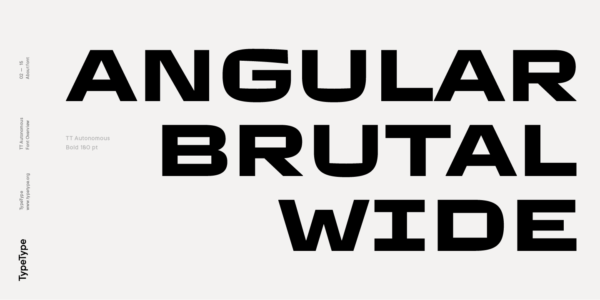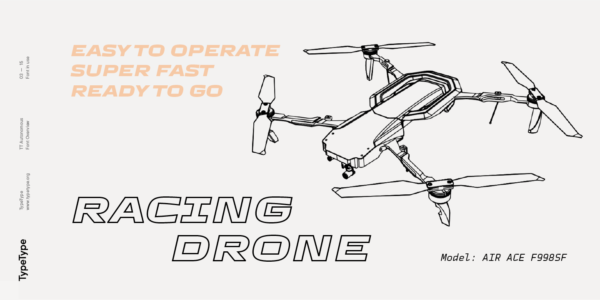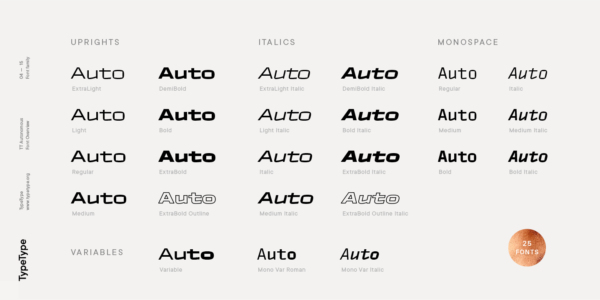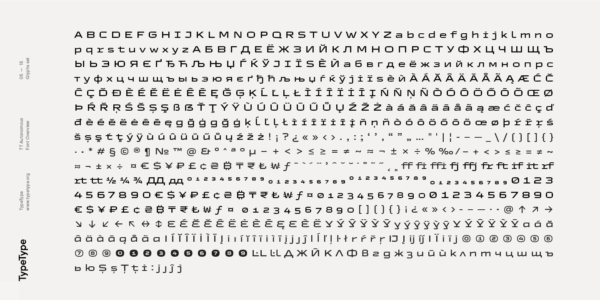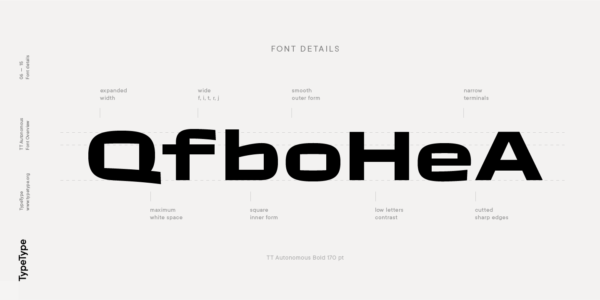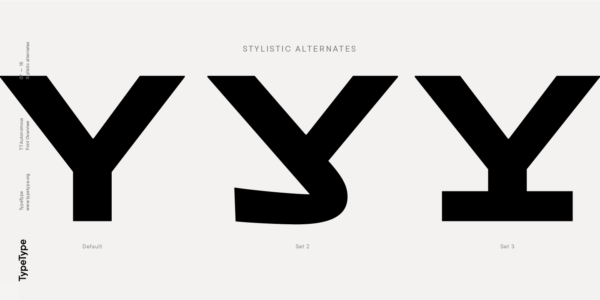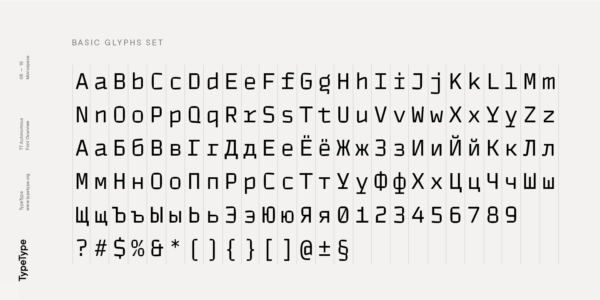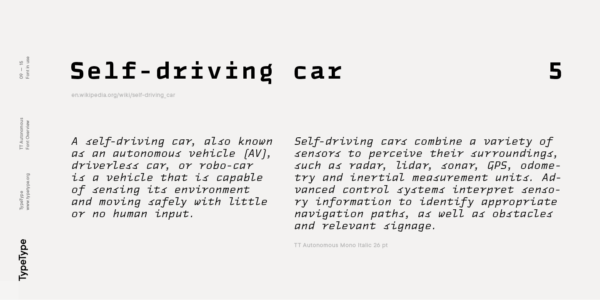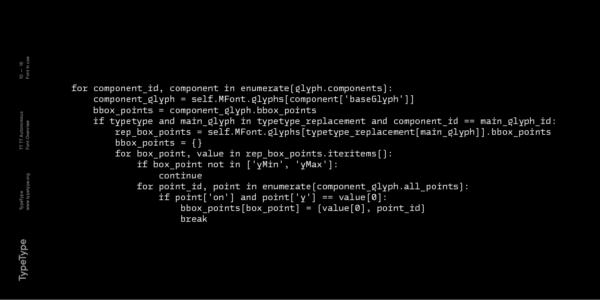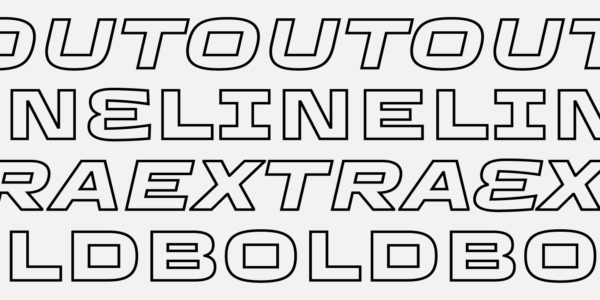
TT Autonomous
TT Autonomous — ТТ Отонамус
Произносится «ТТ Отонамус». «Autonomous» в переводе с английского «автономный». Буквы «TT» являются аббревиатурой названия компании.
TT Autonomous — брутальный технологический гротеск со сквадраченными формами. В гарнитуру входит моноширинное подсемейство, которое можно использовать для кодинга.
Современный брутальный технологичный гротеск
Идея проекта зародилась в Амстердаме, когда одна из наших коллег ехала на официальном электрическом такси аэропорта Схипхол. В тот момент мы как раз размышляли о создании нового широкого гротеска и во время этой поездки вдруг возник интересный вопрос — а какой шрифт мог бы ассоциироваться с электрическим беспилотным транспортом и, кроме того, хорошо дополнить эту тему с визуальной точки зрения.
В гарнитуре TT Autonomous есть вариативная версиякак обычной гарнитуры, так и моноширинного семейства.
14 начертаний, 6 моно, 2 аутлайн и 3 вариативных шрифта
О гарнитуре TT Autonomous
Идея проекта зародилась в Амстердаме, когда одна из наших коллег ехала на официальном электрическом такси аэропорта Схипхол. В тот момент мы как раз размышляли о создании нового широкого гротеска и во время этой поездки вдруг возник интересный вопрос — а какой шрифт мог бы ассоциироваться с электрическим беспилотным транспортом и, кроме того, хорошо дополнить эту тему с визуальной точки зрения.
Таким образом на свет появилась гарнитура TT Autonomous, которая является современным брутальным технологичным гротеском. Основной визуальной характеристикой гарнитуры является заметная сквадраченность знаков и угловатое внутреннее пространство. Кроме того, пропорции основного шрифта стремятся к тому, чтобы выглядеть моноширинными, не являясь такими на самом деле. Сама ширина знаков вдохновлена пропорциями автомобильных логотипов, которые в большинстве своем довольно широкие.
Мы не могли обойти стороной тот факт, что строчки кода в ПО беспилотных автомобилей по традиции набираются моноширинными шрифтами, и добавили специальное моноширинное подсемейство в гарнитуру TT Autonomous. За счёт сквадраченности знаков, наследуемой из основного подсемейства, и непосредственной моноширинности, формы знаков в этом подсемействе получились очень интересными и характерными. В особенности это относится к наклонным моноширинным шрифтам, которые представляют из себя настоящий италик.
Кроме того, мы сделали пару аутлайн начертаний, которые отлично подходят для использования в заголовках и крупных надписях и которые отлично сочетаются с базовым семейством и с моноширинным подсемейством. В отличии от аутлайнов, которые получаются в графических редакторах, в TT Autonomous Outline мы проработали все узкие и спорные места, благодаря чему шрифт выглядит профессионально законченным и гармоничным.
Так как гарнитура с самого начала разрабатывалась с ориентацией на технологии завтрашнего дня, мы не могли обойти тему вариативности и не сделать сверхсовременный вариативный шрифт. В гарнитуре TT Autonomous есть вариативная версия как обычной гарнитуры, так и вариативная версия моноширинного семейства.